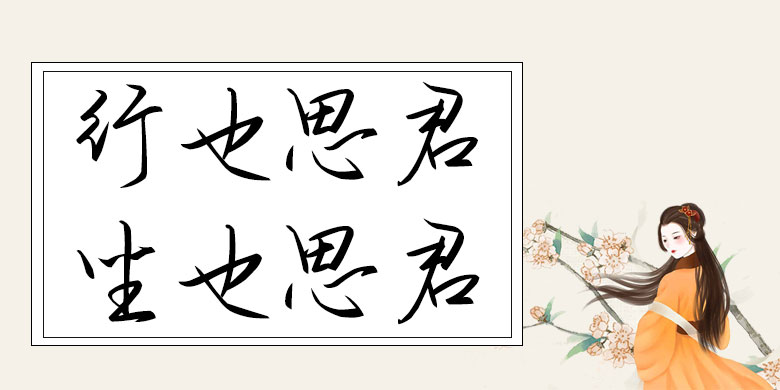
品牌:方正手迹设计师:刘殿儒发行时间:2019字库编码:大陆简体(GB2312-80)分类:常规书写·硬笔字体属性:精品字
该字体的创作灵感来源于唐寅的《雨打梨花深闭门》,因对诗中浓浓相思之情有感而作。该字逸美畅然,清晰明朗。转折处坚定有力,回锋时行笔迅捷,横撇竖捺中尽显秀骨清透。疏密得当,布白匀称,灵动洒脱,如“晓看天色暮看云”之境,令人赏心悦目。适用于现代诗歌、短文的排版以及文化、商业类品牌的广告语设计。